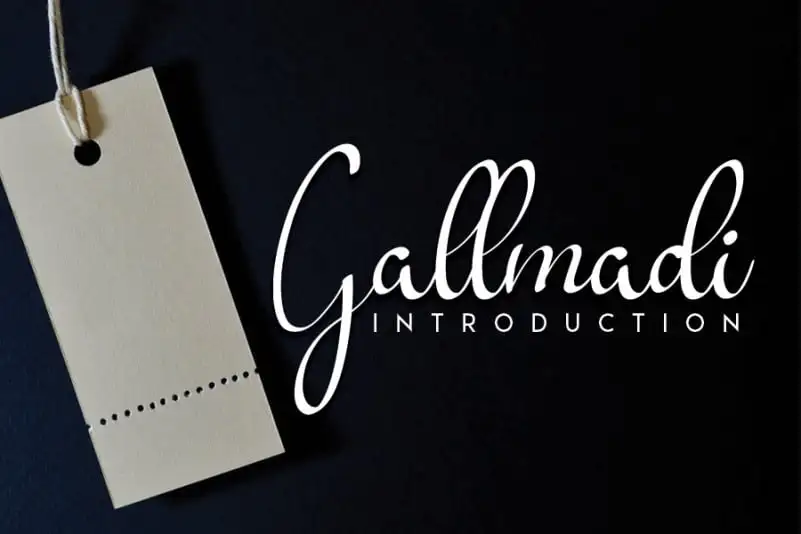
Gallmadi Calligraphy Font – Fonte Grátis
Gallmadi Calligraphy Font
A Gallmadi Calligraphy Font é a escolha perfeita para quem busca simplicidade no encanto do estilo elegante dos caracteres góticos manuscritos. Através dela, você pode traduzir elegância de maneira única e sofisticada em seu design gráfico. Esta fonte mantém seus influências chamigoticas respeitando sua classe enquanto traz uma sensação contemporânea e moderna que faz da Gallmadi Calligraphy Font um verdadeiro farol para ideias criativas. Seja para criar cartões de letterhead, títulos ou até mesmo itens de papelaria, a versatilidade desta fonte atende todos os seus requisitos. É uma escolha perfeita para designers que valorizam tanto estilo quanto simplicidade.